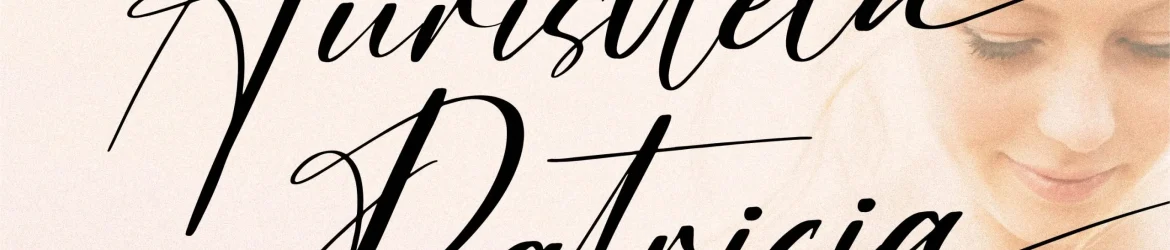
Auristtela Patricia Font – Fonte Grátis
Auristtela Patricia Font
A Auristtela Patricia é uma fonte de registro premium projetada para trazer personalidade ao seu trabalho de design. Ideal para projetos que exigem um toque de luxo e sofisticação, esta fonte se destaca como a escolha perfeita para criar identidades visuais icônicas, embalagens de produtos elegantes, cartões de nomeador chamativos e materiais promocionais de qualidade. Suas linhas delicadas e sutilezas proporcionam uma versatilidade única, permitindo-lhe usar o Auristtela Patricia para variados projetos que exijam um toque distintivo. Seja você designer gráfico, produtores de material promocional ou editor de imagens, a Auristtela Patricia é sua aliada perfeita em busca da criação de designs únicos e premium.